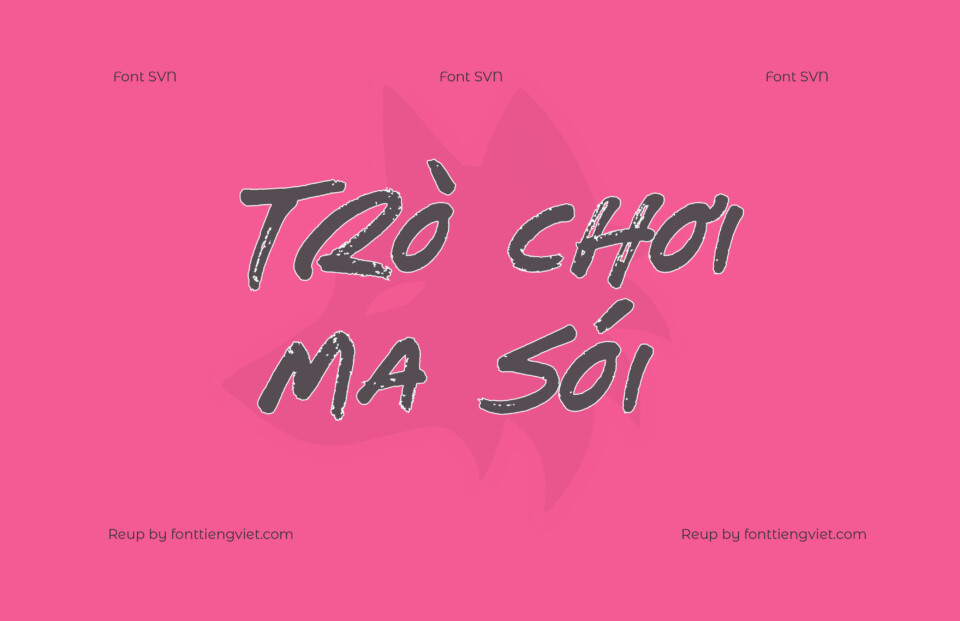
Font Việt hóa SVN Timber Wolf
Giới thiệu về Font Việt hóa SVN Timber Wolf
Trong thế giới sáng tạo đồ họa, việc tìm kiếm một bộ Font Miễn Phí chất lượng luôn là ưu tiên hàng đầu của các bạn học sinh và giáo viên. Font Việt hóa SVN Timber Wolf nổi bật như một làn gió mới mang phong cách mạnh mẽ, bụi bặm nhưng không kém phần tinh tế. Đây là bộ font được thiết kế với những đường nét thô mộc, mô phỏng nét vẽ tay tự nhiên, giúp các bài thuyết trình hay báo tường trở nên sinh động và có chiều sâu hơn. Việc sử dụng Font Việt hóa SVN Timber Wolf giúp người xem dễ dàng cảm nhận được sự phóng khoáng và cá tính riêng biệt trong từng tác phẩm nghệ thuật.
Ưu điểm nổi bật của bộ font chữ này
Thiết kế độc đáo và linh hoạt
Font Việt hóa SVN Timber Wolf sở hữu các ký tự được chăm chút kỹ lưỡng, đảm bảo tính thẩm mỹ cao khi ứng dụng vào nhiều loại hình thiết kế khác nhau. Từ việc làm tiêu đề sách, thiết kế áo đồng phục lớp cho đến các biểu ngữ sự kiện tại trường học, font chữ này đều phát huy tối đa khả năng thu hút thị giác. Đặc biệt, bảng mã đã được tối ưu hóa hoàn toàn cho tiếng Việt, giúp bạn viết có dấu mà không lo lỗi font hay sai lệch khoảng cách giữa các chữ cái.
Dễ dàng sử dụng trên nhiều nền tảng
Kết luận về Font Việt hóa SVN Timber Wolf